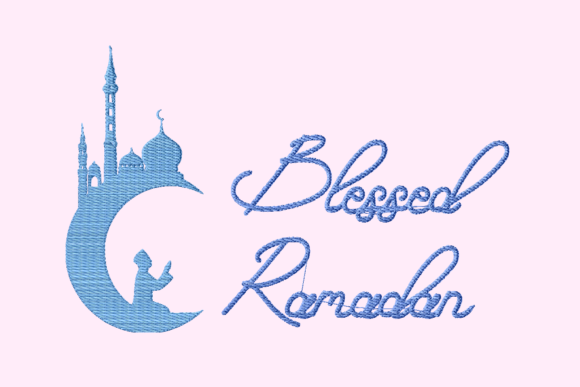
Blessed Ramadan
適切なデザイン要素を見つけるのは難しい場合がありますが、Blessed Ramadanは作品を即座に引き立てる優れたコレクションを提供します。
POD(オンデマンド印刷)製品、結婚式の招待状、またはソーシャルメディアのグラフィックを作成している場合でも、Blessed Ramadanは理想的です。